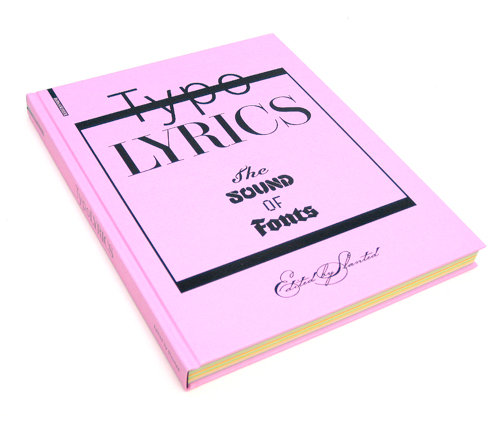
176 visuelle Kompositionen – wir freuen uns sehr, das Projekt »TypoLyrics – The Sound of Fonts« welches im Birkhäuser Verlag erschienen ist vorzustellen zu können. Das Konzept der TypoLyrics resultiert aus der gleichnamigen Rubrik des Slanted Magazin und lässt sich als Versuchsanordnung, in der Musik, Songtexte und Typografie in einem Visual zusammengebracht werden beschreiben. Die Publikation versammelt über 170 solcher Beiträge, die von ebenso vielen Grafik- und Schrift-Designern eigens dafür erstellt wurden und so zu einem eindrucksvollen Gesamtwerk beigetragen haben.
In 11 Kapiteln werden verschiedene Musik-Genres von Klassik bis Krautrock, von Swing bis Punk mit geläufigen Schriftgattungen und zeitgenössischen Font-Designs konfrontiert. Dabei haben diese Kombinationen die eingeladenen Designer vor reizvolle Herausforderungen jenseits des persönlichen Geschmacks oder visueller Vorlieben gestellt. Die überaus sehenswerten Ergebnisse stellen eine Sammlung einmaliger Design-Experimente zwischen Sound und Fonts dar.
Redaktionell werden die TypoLyrics durch Beiträge von Max Dax, Chefredakteur des Spex-Magazins und dem DJ und Produzenten Frank Wiedemann untermauert bzw. kommentiert. Desweiteren geben Dirk Rudolph, StyloRouge und
Invisible Creature anhand von Interviews einen Einblick in den beruflichen Alltag und ihre Erfahrungen zwischen akustischer und visueller Gestaltung.
Das Buch ist als Hardcover erhältlich – Besonderheit ist das pro Kapitel wechselnde, durchgefärbte Papier (IQ color, 120 g/qm) von Mondi und die jeweils variierenden Sonderfarben. Gedruckt und produziert wurden die Publikation von E&B Engelhardt und Bauer in Karlsruhe.
Die TypoLyrics verstehen sich auf Grundlage der Visuals und Schriftübersichten als Informations- und Inspirationsquelle für Grafikdesigner, Typographen und Musikliebhaber.